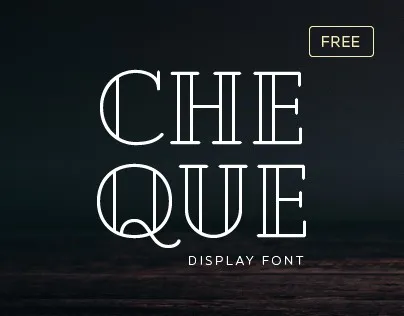
A Cheque Display Font é uma opção única para quem busca um estilo elegante e vintage para suas aplicações visuais. Criada pela fantástica designer Mirela Belova, essa fonte premium está disponível na Fontfabric e pode ser encontrada no site da MyFonts. A fonte chega a nossas mãos através de uma paleta de cores geométricas que converte textos em designs clássicos e modernos ao mesmo tempo. Se você deseja criar layouts para publicidade, materiais de marketing ou qualquer outro tipo de aplicação visual onde um look vintage seja o destaque, a Cheque Display é perfeita. Suas linhas retas e formas geométricas criam uma aparência sofisticada e moderna que se tornará sua aliada em projetos que exigem um impacto imediato e poderoso. A fonte funciona melhor para headlines e composições, combinando de forma harmoniosa com qualquer tipo de texto. Além disso, a versão Regular é gratuita tanto para uso pessoal quanto comercial, o que torna ainda mais valiosa essa opção. Não hesite em experimentar a Cheque Display Font na sua próxima criação visual. Essa fonte certamente deixará um sabor de aventura e sofisticação no seu trabalho final.